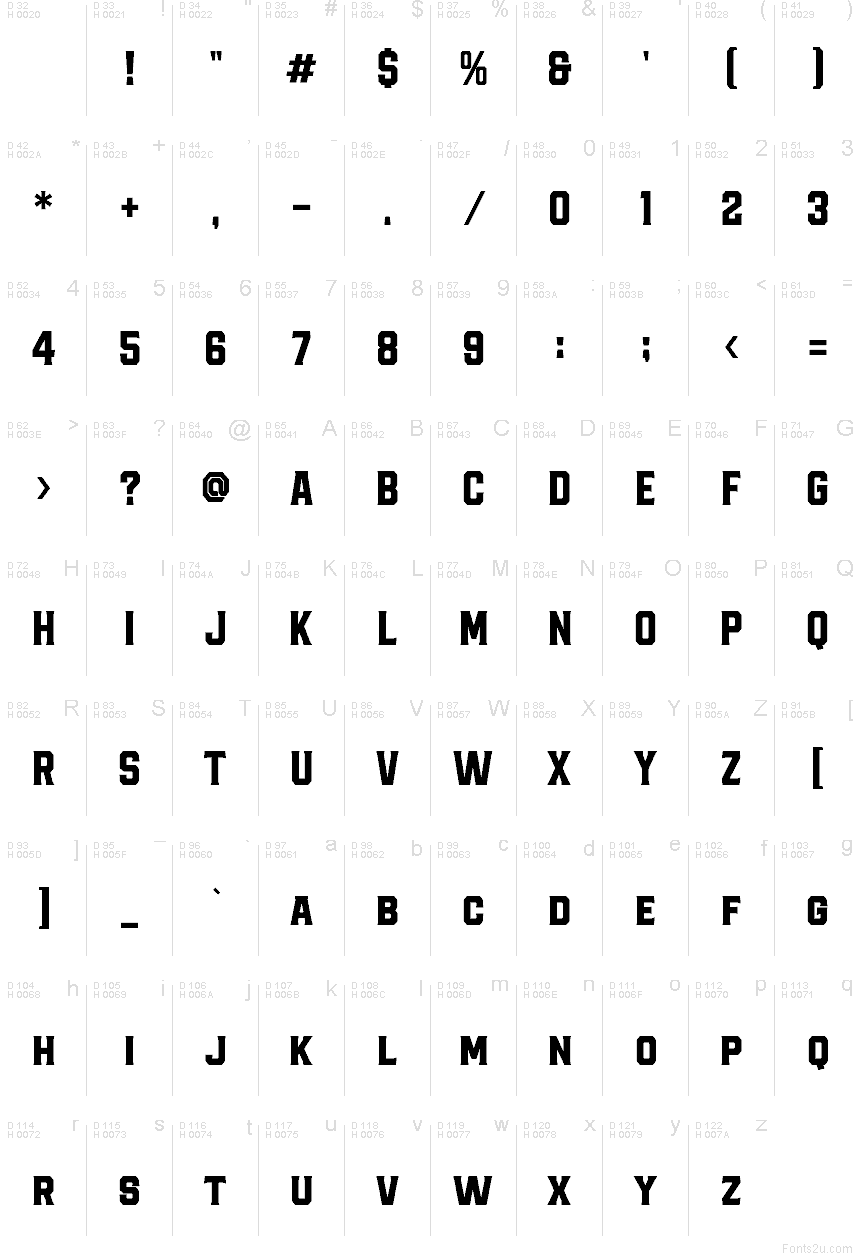
Thomkit Strike Serif, da Blankids Studio, é uma fonte display serifada retrô gratuita que traz o estilo robusto das antigas marcas esportivas e das letras de uniformes vintage. Suas maiúsculas parecem entalhadas e compactas, com formas de bloco pesadas, entalhes profundos e cortes triangulares nítidos que conferem vida às letras, em vez de apenas um preenchimento sólido.
Isso a torna uma escolha natural para títulos de cartazes, logotipos, embalagens, capas de álbuns e cartões de título onde você precisa de uma fonte gratuita com um tom mais forte e nostálgico. Ela também funciona muito bem para cabeçalhos curtos ou iniciais em estilo monograma, já que as letras possuem forma e contraste suficientes para prender a atenção com apenas alguns caracteres.